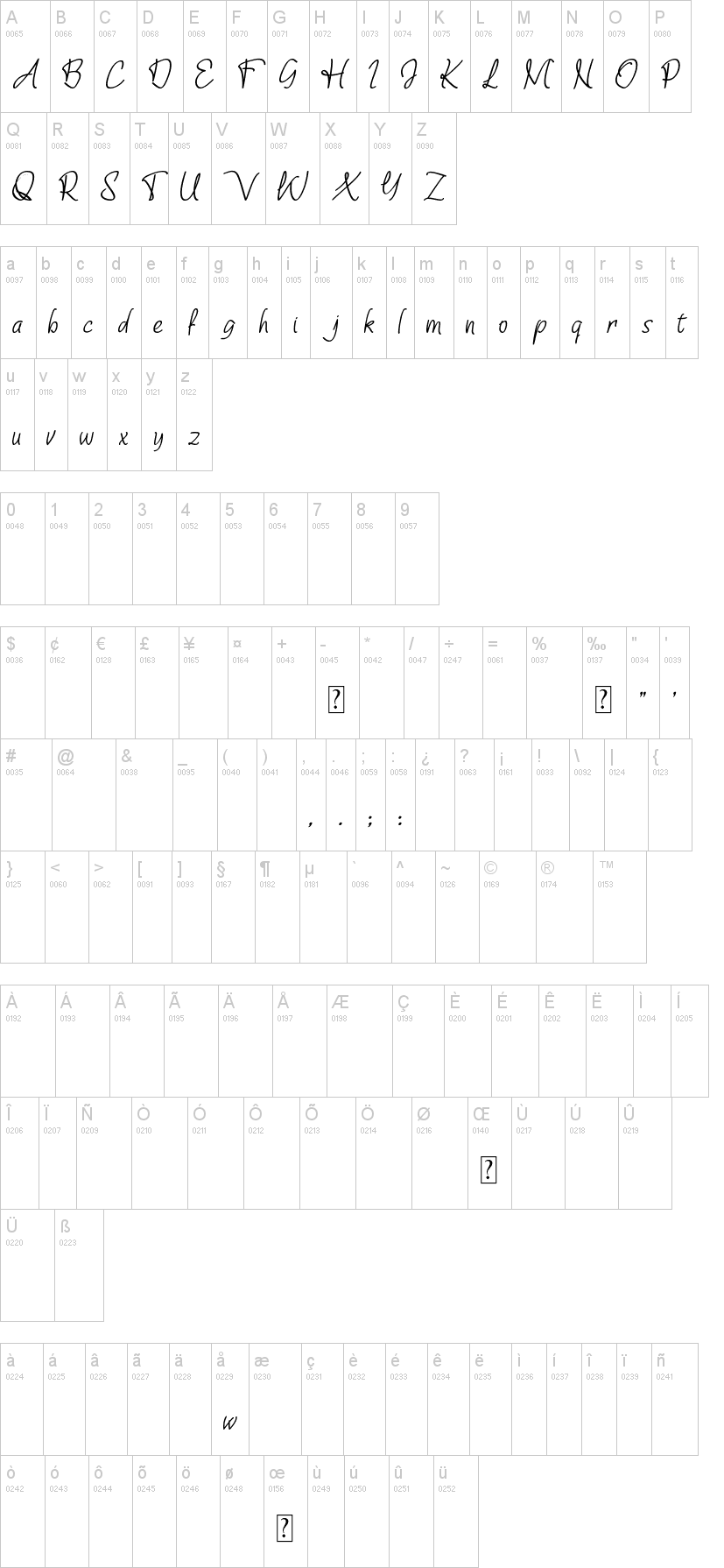
Shevana
Shevana 字体是一个简洁的楷体字体,由埃及设计师 Shevana 创作。它的特点是笔画粗细均匀,结构紧凑,每个字母都拥有自己独特的风格,使字体显得更加立体。它的字形优美,笔画流畅,带有一种古典的复古风格,非常适合用于海报、书籍和网页等设计。
Shevana是一款非常不错的手写艺术字体,具有很好的视觉感,适合于文化类的宣传设计、商业类品牌的广告和产品包装设计以及个性化文字排版等较多场景。
Shevana字符映射图